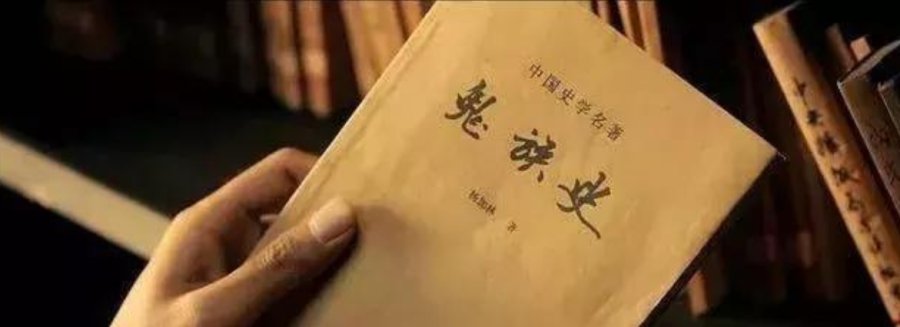
《九层妖塔》中的剧照
向佳红起诉时称,电影《九层妖塔》中有七个字采用了其创作的字体,分别是鬼、族、史、华、夏、日、报。而《鬼族史》与《华夏日报》道具在影片中占有主导分量,是剧情的重要组成部分。
近日,北京知识产权法院对《九层妖塔》字体侵权案作出二审判决,该影片制作、发行、网络传播方等4被告公司因在未经授权的情况下,在电影中使用了书法家向佳红创作的字体,被判共同赔偿向佳红经济损失等14万元。12月13日,向佳红向南都记者表示,其于当日收到了委托律师发来的二审判决书,起诉并不完全是为了获得经济赔偿,主要是得到尊重。“字体创作是一项漫长艰辛的工作,需要投入大量精力,因次商业用途必须获得授权。”
2015年,电影《九层妖塔》上映,该影片改编自小说《鬼吹灯之精绝古城》。随后,向佳红发现电影《九层妖塔》中出现了自己创作的“向佳红毛笔行书”字体,但该使用行为并未经过其授权。随后向佳红以侵犯著作权为由,将梦想者电影(北京)有限公司、北京环球艺动影业有限公司、乐视影业(北京)有限公司及中国电影股份有限公司诉至法院,索赔版权使用费50万元、精神抚慰金1万元。
据南都此前报道,向佳红起诉时称,电影《九层妖塔》中有七个字采用了其创作的字体,分别是鬼、族、史、华、夏、日、报。而《鬼族史》与《华夏日报》道具在影片中占有主导分量,是剧情的重要组成部分。“但我并未授权任何单位和个人使用‘向佳红书法字体’,更未允许任何单位和个人将字体用于商业营利和传播。”向佳红称,其在此套字体的属性中明确注明,该字体仅限于学习与交流使用,对个人用户免费,但商业用途须需经其本人授权。2013年12月,向佳红向广东省版权局申请作品名称为“向佳红毛笔行书字体”的作品著作权登记。
一审中,被告方辩称,涉案字体不是向佳红创作的,其对此不享有著作权;涉案单字仅出现在电影道具中,目的仅为说明道具名称,为汉字基本使用方法,在于传递其所承载的中文语言含义,而非主要展示其作为美术作品的艺术价值。此外,该使用方法使涉案单字具有了新的意义及功能,未影响其作为美术作品的正常使用,属合理使用。
一审法院经审理认为,向佳红主张权利的7个单字在断笔方式、布局结构、笔画粗细等方面均体现出了独特的美感。呈现出了不同于传统行书及其他常见字体的独创性表达,融入了书写者独特的智力判断和选择,属于我国著作权法中规定的美术作品。最后,四被告被判共同赔偿向佳红14万元。
一审判决后,梦想者电影(北京)有限公司、中国电影股份有限公司继续提起上诉,认为《九层妖塔》中对向佳红主张权利的7个单字的使用未违背其创造意图,其使用属于对涉案做转化性使用。同时,电影中对涉案作品使用仅作为道具的组成部分,在影片中短暂出现,如果署名会破坏电影画面的完整性。
二审法院经审理认为,电影拍摄过程中对涉案7个单字的使用属于复制行为,该行为未得到权利人的许可,即侵犯了著作权中的复制权,也不属于合理使用。最终,驳回上诉,维持原判。